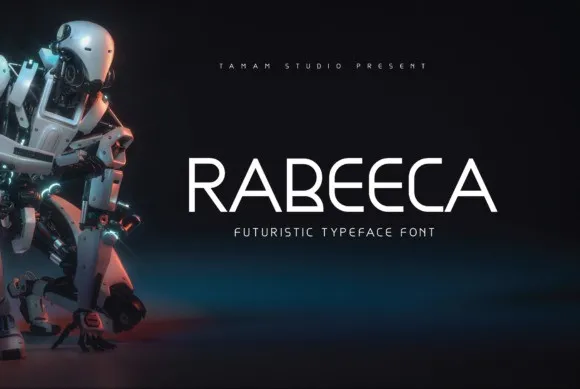
A fonte Rabeeca Font é uma elegante seleção do gênero Display para designers criativos apaixonados por fazer projetos distintivos. Criada pela Tamam Studio, esta fontes sans-serif incorpora algumas curvas suaves que tornam-a ainda mais amigável e levemente aconchegante. Suas linhas arredondadas dão ao texto um tom descontraído e moderno. Rabeeca é uma escolha perfeita para se juntar à sua criatividade, já que o destaque dado por esta font não só enriquece seus projetos, mas também torna-os verdadeiramente únicos e imprimíveis. Seja em design gráfico ou publicidade, a Rabeeca é uma escolha inteligente para agregar valor aos seus ideais de criatividade.